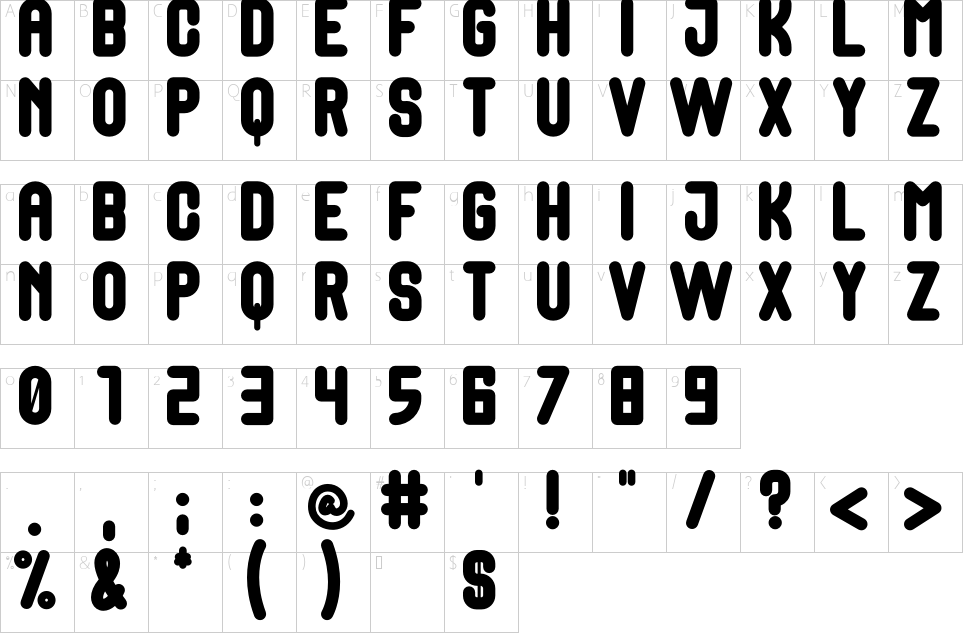
Eathoma Sans Serif Font – Download Grátis
Descubra Eathoma Sans Serif, uma elegante fonte serif sem ser quadrada para sua próxima projeto gráfico ou digital. Desenvolvida pela Jadatype e disponível gratuitamente tanto no Windows quanto Mac, Eathoma Sans Serif oferece um equilíbrio perfeito entre modernidade e sofisticação. Com 16.140 downloads atingidos, a comunidade de designers já testemunhou sua capacidade de criar estilos distintos em projetos diversos. Seja para websites, aplicativos móveis ou materiais impressos, Eathoma Sans Serif não só preenche sua necessidade sem comprometer o seu estilo único. Descubra por si mesmo, e experimente os benefícios desta fonte única e versátil.